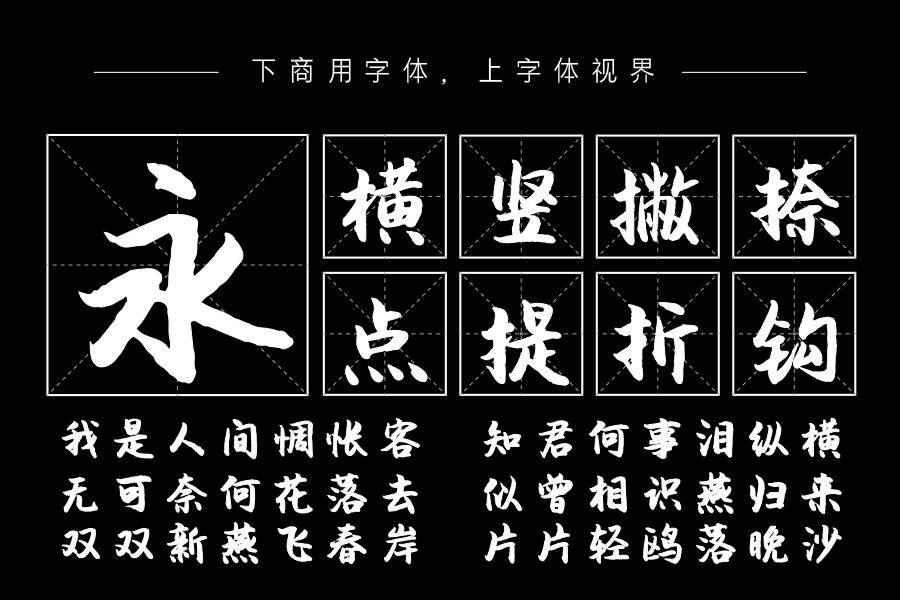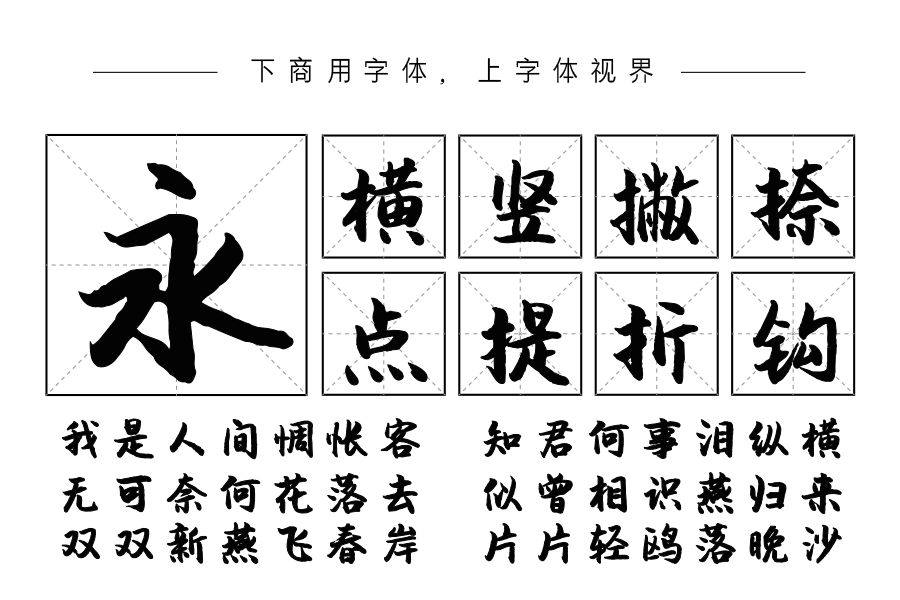
润行的笔法因笔的触觉略带写经起笔风,因显和润,顾得此名。其字形对称、笔画饱满,多用于各类标题,尤适于各类人文类题材。购买须知:“下载服务费”与“字体VIP”所获得字体 仅用于个人非商用, 商用请联系付费授权。本字体为电脑用字,手机没有root权限不支持直接手机换字(手机如何root,请自行百度搜索教程)。购买前请先 了解清楚后再付款 ,字体为虚拟产品无法回收 一旦购买不支持退款。